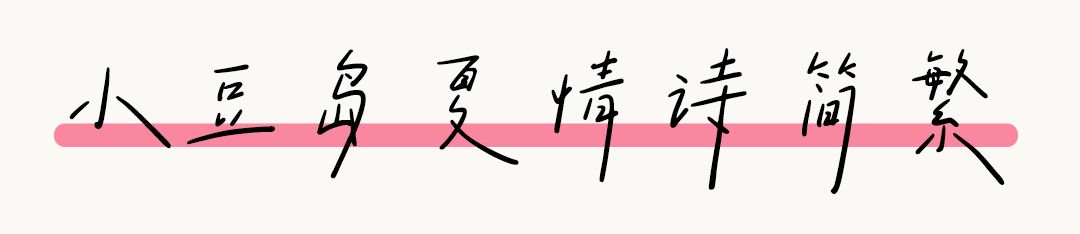
清新文艺手写字体—小豆岛2款字体上线!
清新文艺手写字体—小豆岛2款字体上线!,这款字体结构工整、笔画清晰,兼顾美观与易读性,适用于标题、正文、海报、包装、LOGO 等多种场景。字形优雅稳定,风格百搭耐看,适配日常排版与创意设计,让文字呈现更舒适、更具质感。清新文艺手写字体—小豆岛2款字体上线!一笔一画,皆是细节,以均衡的比例、流畅的线条打造舒适视觉体验,字形端正大气,风格简约现代。无论是商业设计、品牌宣传还是日常排版,都能轻松驾驭,让文字更有格调与力量。清新文艺手写字体—小豆岛2款字体上线!字体下载。
这部入围影片《夏日南风》
由小豆岛白南风 X 夏情诗
两位手写字体新人字导字演
小豆岛白南风
是一位清新自然的手写字体新人
笔画简洁,明快轻盈
字游洒脱,青春文艺
听海风擦身过 看浮云卷又舒
小豆岛夏情诗
是一位风雅怡然的文艺字体新人
字形细挑 青春慵懒
书写关于夏天的风情诗
小豆岛白南风简繁
风格气质:文艺,清新,可爱,二次元
小豆岛夏情诗简繁
风格气质:文艺,清新,可爱,二次元